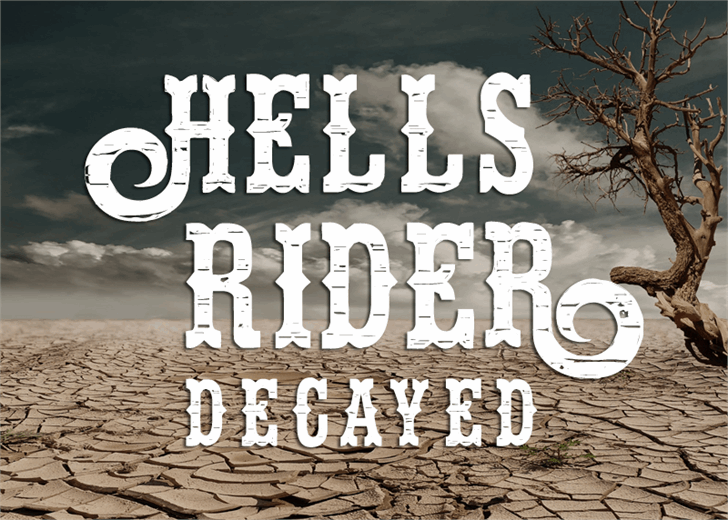
Hells Rider Decay Font
A Font Hells Rider Decay é uma deliciosa opção para designers que buscam adicionar um toque único a seus projetos visuais. Disponível em versão licenciada, ela oferece estilos sólidos e destruídos numérica e graficamente, perfeita tanto para uso pessoal quanto para alguns tipos de projetos profissionais, mas sem direitos autorais sem uma licença. Através deste estilo chamado Hells Rider Decay, você pode explorar a riqueza e a complexidade em cada letra, criando designs dinâmicos que se destacam no meio do conjunto visual. Não perca tempo: com um designer experiente como o Font Monger, a qualidade dessa font é garantida para qualquer projeto ou design que deseje dar vida.